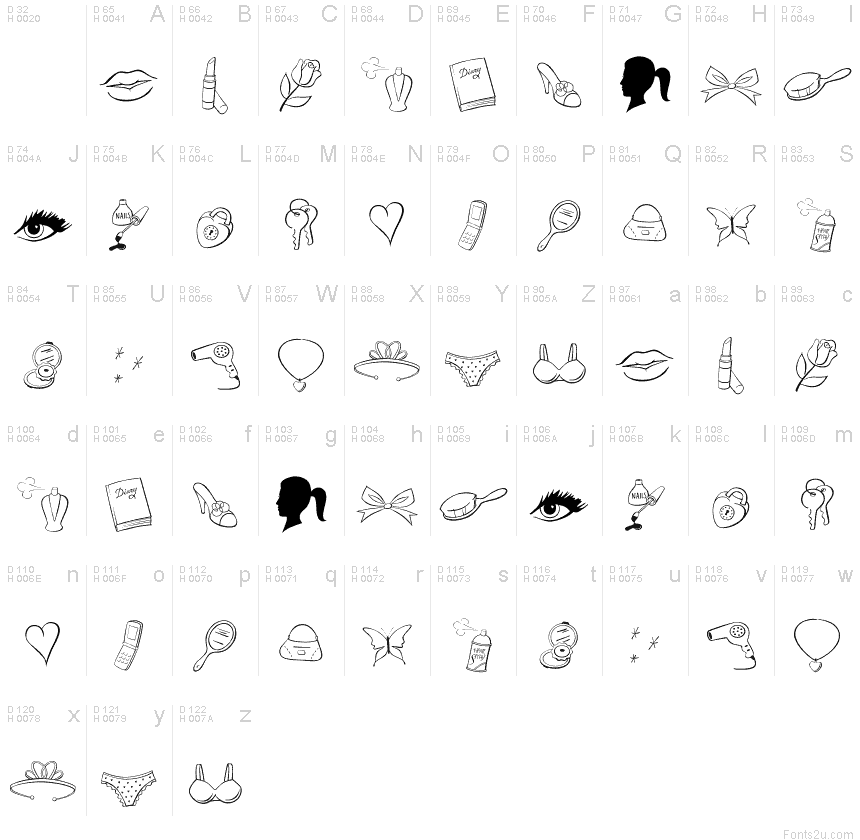
Princess od BV Fonts je bezplatné kreslené dingbat písmo vytvořené z jemných čárových kreseb ženských a pohádkových objektů. Symboly mají vzdušný, ručně kreslený vzhled s tenkými obrysy, jemnými křivkami a drobnými vnitřními detaily, které udržují kolekci vizuálně soudržnou.
Designéři tvořící pro mladé fanoušky fantasy mohou tyto obrázky využít na pozvánkách na párty, v dětských publikacích a tématickém merchi. Mohou fungovat jako samostatné ilustrace nebo se opakovat jako lehký dekorativní vzor, namísto toho, aby sloužily pouze jako psané symboly. Motýli, srdíčka, květiny a osobní doplňky dělají tuto sadu obzvláště vhodnou pro příběhy o princeznách a převlekové motivy, čímž propojují písmo přímo s daným tématem.